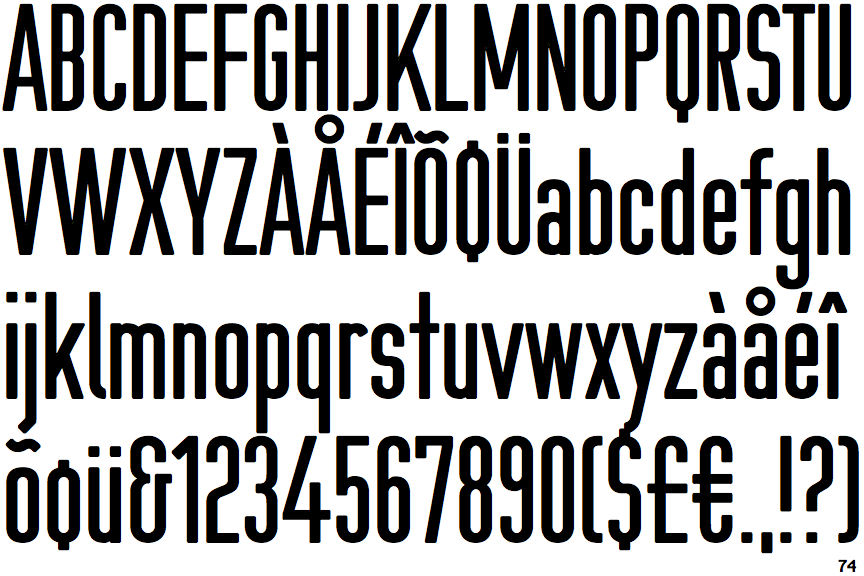
Schrift auf Propaganda-"Plakat"
So konnte es ja nichts werden bei der Schtsch-M! Steht das für Schietisch Meisterschaft?
Aber im ersnst, da hat jemand fix gebastelt, und lateinische mit kyrillischer und auch griecischer Schrift, bei der dem Lambda sann Umlaut-Tütelchen verpasst wurden zurechtgemixt.
Bei den üblichen Verdächtigen habe ich die Schift nicht gefunden.
Wie immer die Frage: woher stammt das? Von der Rückseite scheint ja gesetzter Text in eben dieser Schrift durch, das würde die Suche erleichtern …
da muss ich an folgende - gedanklich über Neufünfland hinaus gen Osten orientierte - Schrift denken:
Typeface: FF Cst Berlin East Original
Designers: Ole Schäfer and Verena Gerlach
Year: 2000
Publisher: FontFont
Ob diese wohl dabei Pate stand? Einfach mal durch die ähnlichen Schriften schauen hat aber leider nix gebracht, siehe:
Danke Uwe, das Könnte die richtige sein. Wenn man aus den Fragmenten dann eine Cyrillische baut könnte es sogar passen.
Herkunft ist Twitter und der Autor bedankte sich bei 11Freunde. Auf der Webseite hab ich jetzt nichts gefunden. Könnte ja eine Beilage gewesen sein.  In der google Bildersuche hatte ich das eingegeben  " löw hummels özil marx engels lenin ". Jetzt wird sich jemand fragen wie ich auf Marx Engels Lenin komme.
Hier die Lösung:  lenin_engels_marx.jpg
der Erstfund war ein Laden oder Büro in Berlin nähe Helmholz-Platz Prenzlauerberg, Berlin
Hier ein weniger extremer Versuch, einer lateinischen Schrift eine kyrillische Anmutung zu geben. Könnte aber auch nur für die Titel der Filmreihe konstruiert sein: https://www.zdf.de/dokumentation/zdfinfo-doku/aufstieg-und-fall-des-kommunismus-das-lange-ende-100.html (bei 0:38)
Auch wenn ich mir nicht vorstellen kann dass ZDF einen FreeFont nutzt hier die Schrift.
Was beim ZDF läuft, muss ja noch lange nicht vom ZDF gemacht sein. Da gibt es Unmengen kleiner Subunternehmer, Agenturen, Freelancer etc. etc. etc. Und die nehmen dann, was am einfachsten/billigsten ist. (Und das gilt natürlich für alle Sender.)
Und vom WDR weiß ich es ja sehr genau, das da auch Freefonts Verwendung finden. Einer meiner "Machwerke" war da in einem Tatort zu sehen. Warum also nicht auch beim ZDF?
Ja:
Ist der Tatort "Schwindelfrei", die verwendete (und um Perschirift-Pünktchen ergänzte) Schrift ist Xayax